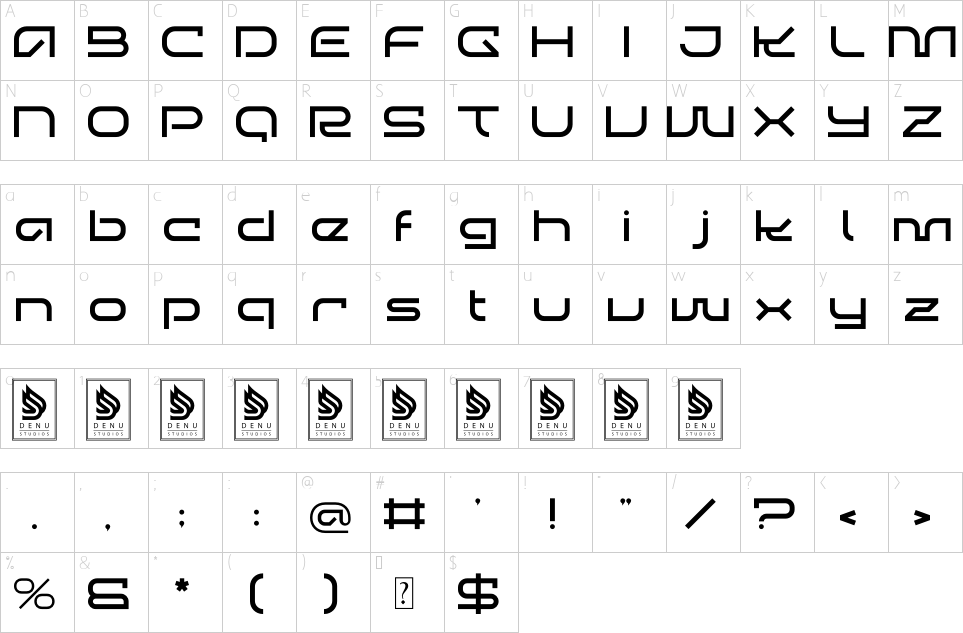
Descubra Gasrox Font, uma elegante e sofisticada opção para sua próxima projeto gráfico. Desenvolvida pelo Denustudios, esta fonte é perfeita tanto para criações de desktop como para dispositivos móveis. Seu design atemporal garante um toque distintivo em seu trabalho. Com mais de 128 downloads confirmados, Gasrox está aí para aqueles que valorizam uma fonte única e versátil para seus projetos digitais. Instale-a no seu sistema Windows ou Mac e experimente a diferença imediata neste conjunto de fontes incrivelmente ricos em detalhes e elegância.